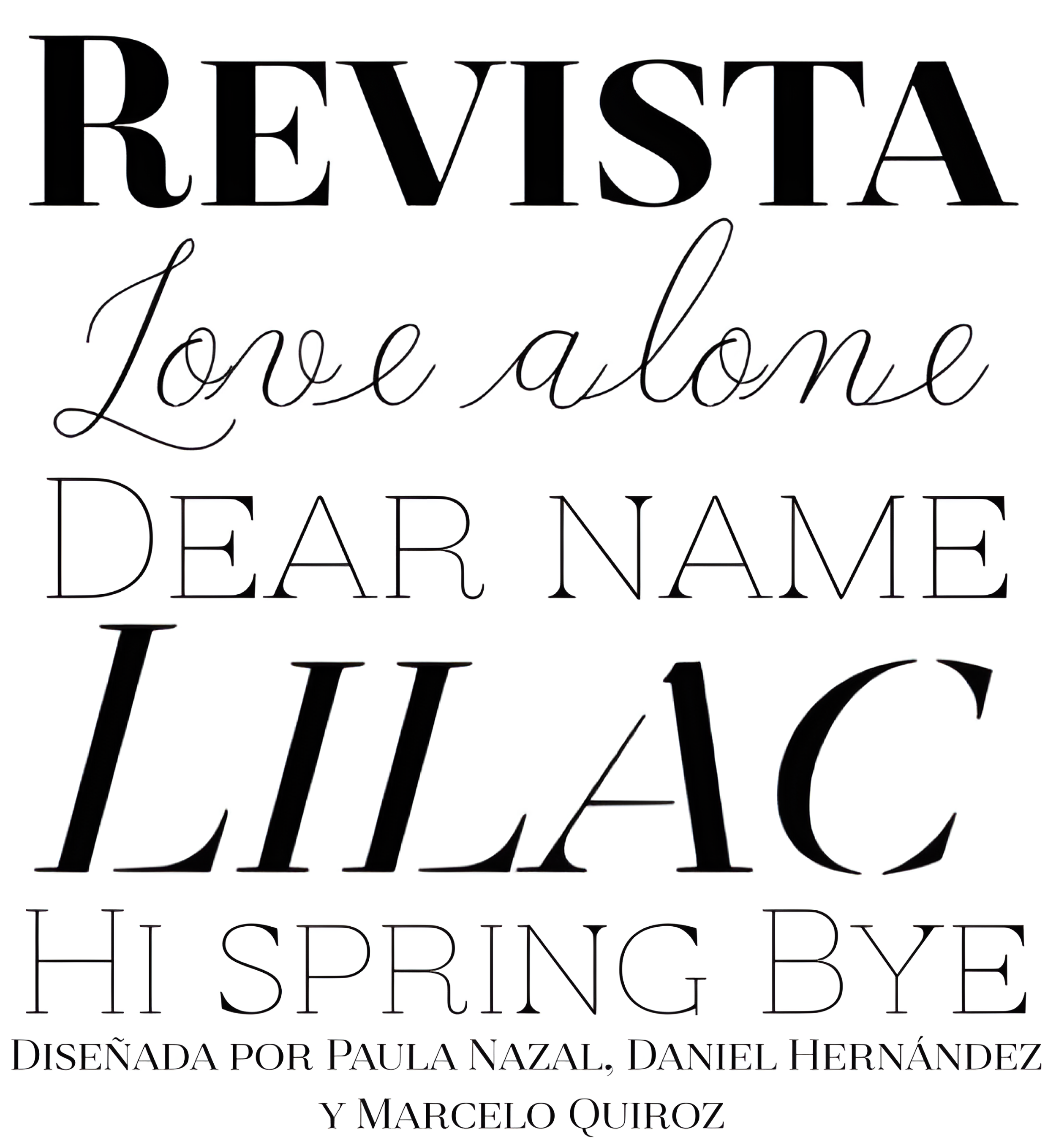
| Descripción | Revista es un sistema tipográfico que reúne todas las características para acometer cualquier proyecto orientado a una revista de moda. La fuente combina armoniosamente diferentes estilos en una única gran familia, que consta de una familia Didone de mayúsculas y versalitas -que incluye 4 variantes que van desde una monolineal Thin hasta una Black con cursivas a juego- y una variante Inline Black que funciona como alternativa decorativa a las fuentes Didone. Revista Stencil, una de sus versiones, viene con el mismo número de variantes. Revista también viene con una familia Script que incluye 5 pesos, desde Thin (monolineal) hasta Black (negro), que contrastan de forma ordenada con muchas ligaduras y alternancias. Puedes elegir entre utilizar alternancias estilísticas -si quieres dar a tus diseños un aspecto desordenado diferente, al estilo de la caligrafía moderna- o alternar entre distintas opciones si buscas un estilo manuscrito. Le recomendamos encarecidamente que utilice las alternancias contextuales predeterminadas y las ligaduras discrecionales para sacar más partido a esta gran familia tipográfica. Revista incluye 2 conjuntos de dingbats, que varían desde símbolos de signos del zodiaco hasta símbolos tecnológicos, y ornamentos complementarios en 3 pesos diferentes: Thin (monolineal), Regular y Black. Todas estas características hacen de Revista un tipo de letra ideal para que los usuarios diseñen a su gusto. |
| Familia(s) | Revista |